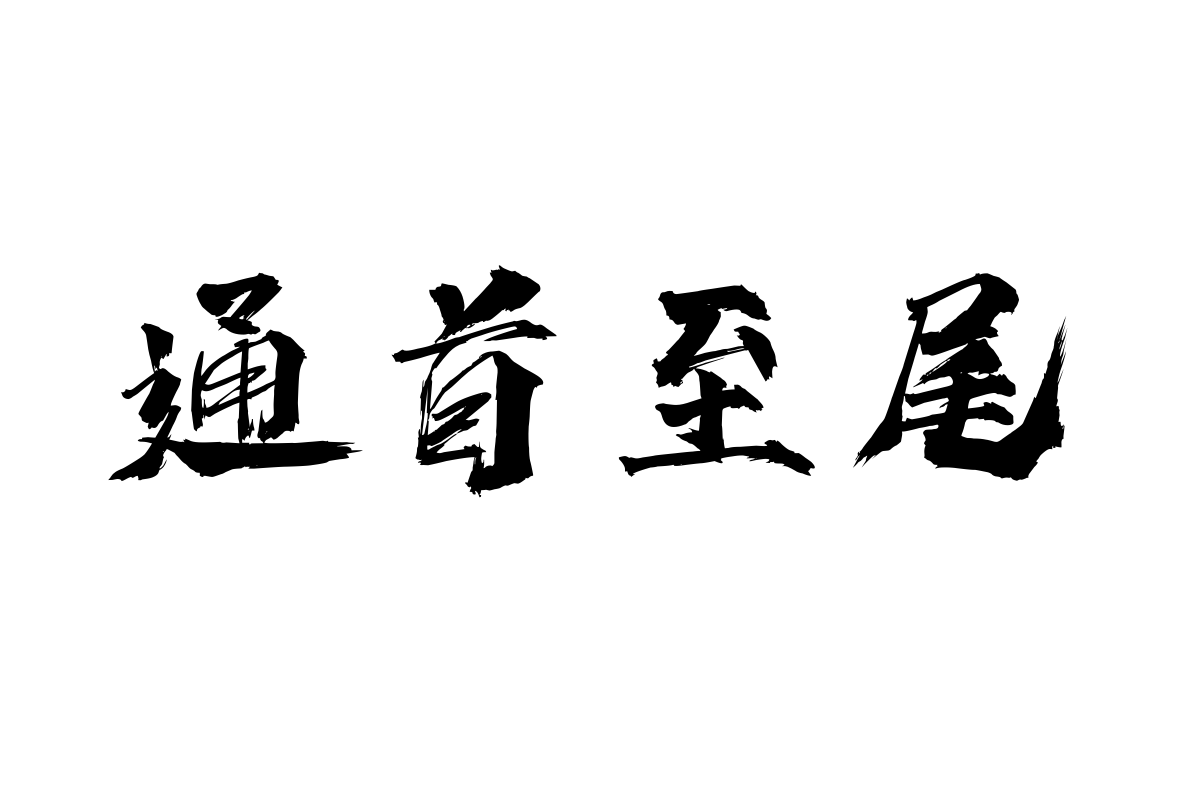
上首疾风书法体是一种独特的字体风格,它以其独特的线条和结构而闻名。这种字体的特点是其笔画的粗细变化较大,给人一种强烈的视觉冲击力。
上首疾风书法体的笔画通常较为粗犷,线条的转折处有明显的弧度,这使得它在视觉上显得更加有力和动感。这种字体的设计灵感可能来自于自然界中的各种形态,如山脉、河流、树木等,因此它的线条往往充满了力量感和生命力。
此外,上首疾风书法体的字间距也相对较大,使得整个字体看起来更加开阔和大气。这种设计使得它在书写时能够更好地展示出作者的个性和情感,同时也使得阅读者能够更好地感受到文字所传达的信息。
总的来说,上首疾风书法体是一种充满力量和动感的字体风格,它以其独特的线条和结构吸引了众多书法家和设计师的喜爱。